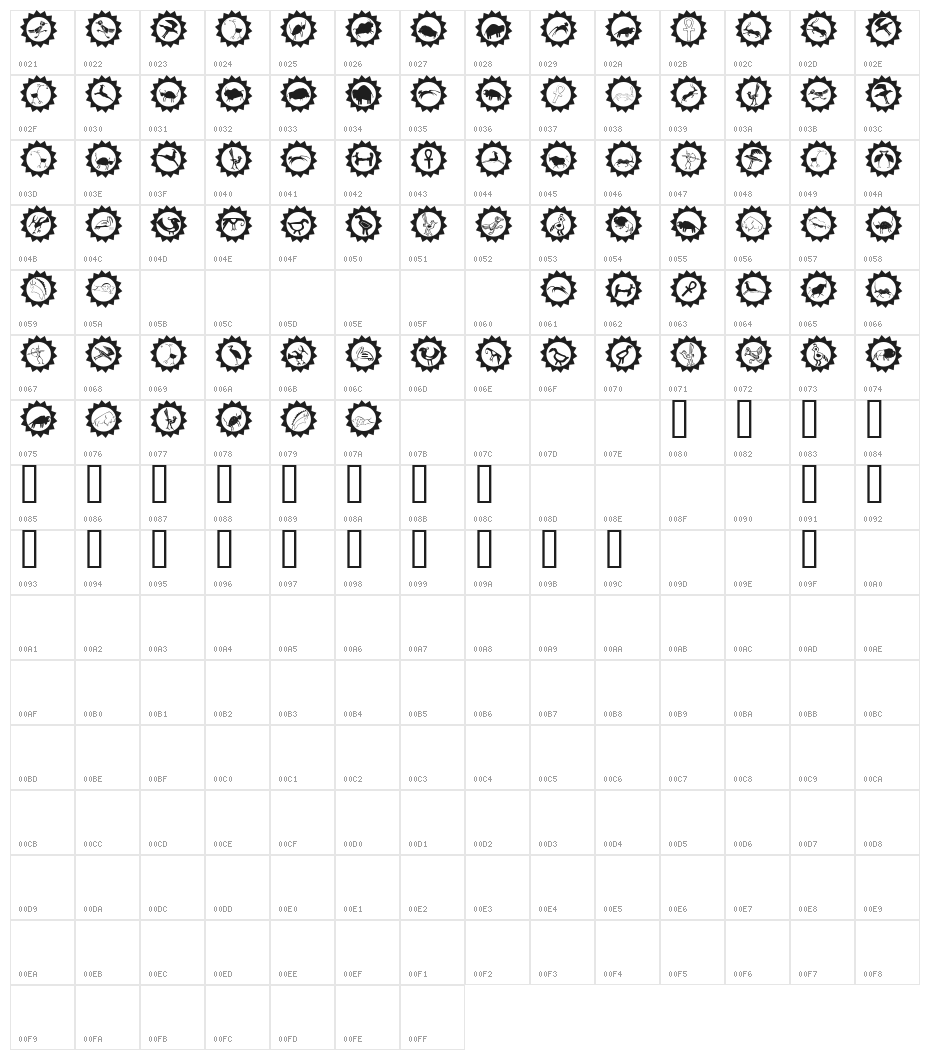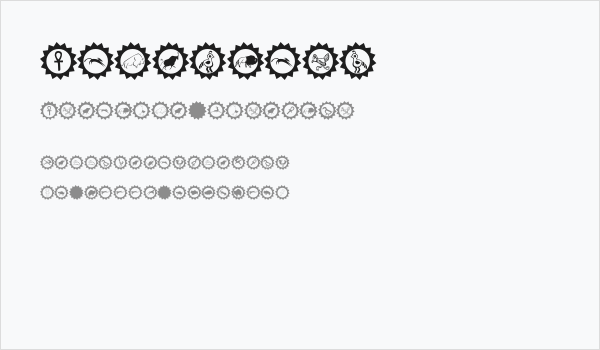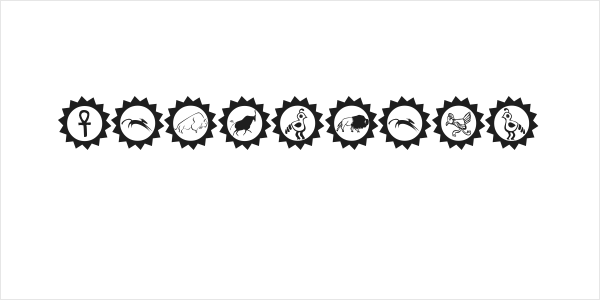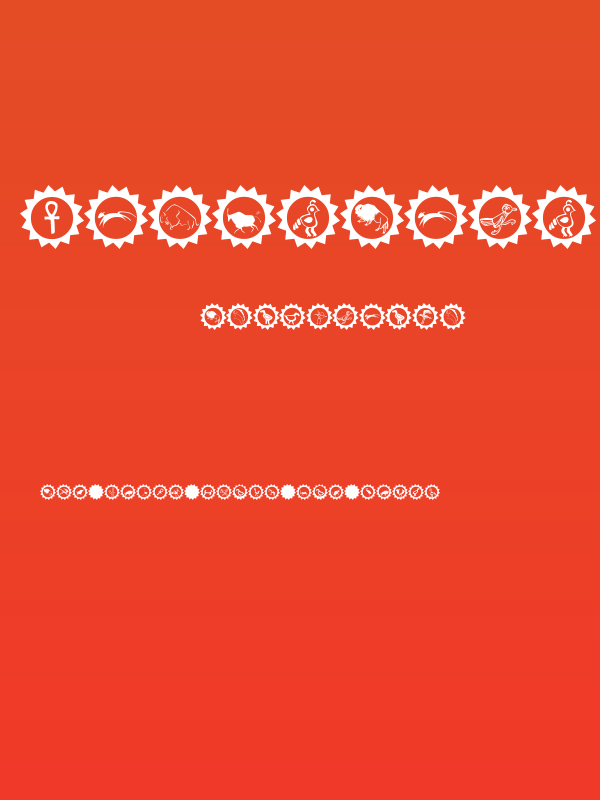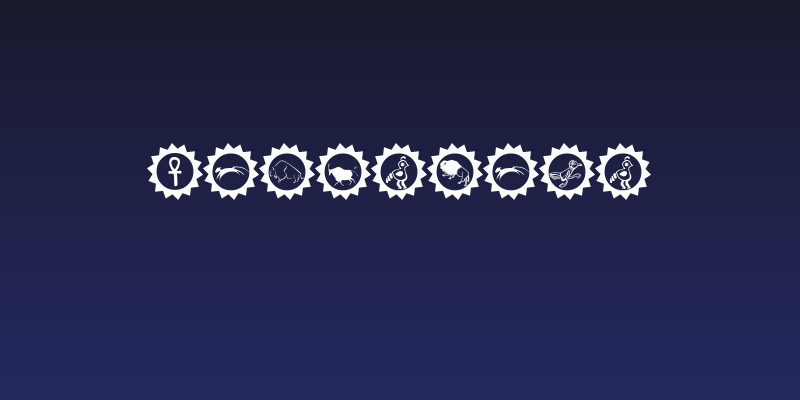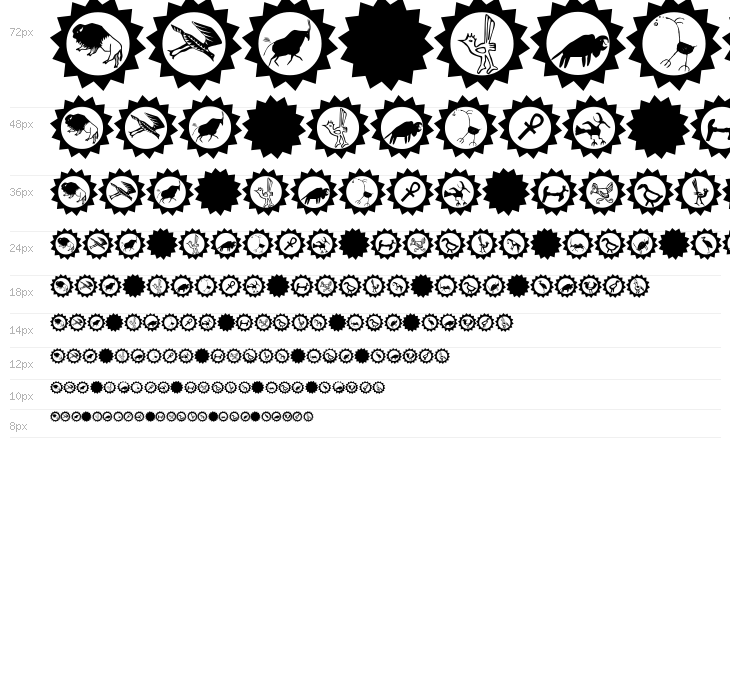
CaveStars Font
CAVESTARS MAIUSCOLE
CAVESTARS MINUSCOLO
CAVESTARS ALTRI CARATTERI
| Stile generale | Decorative, Primitive, Playful |
| Caso d'uso | Logos, Posters, Themed Headlines, Educational Materials |
| Progetti proposti | Children’s books, educational posters, themed party invitations, museum exhibits, prehistoric or adventure branding, creative crafts. |